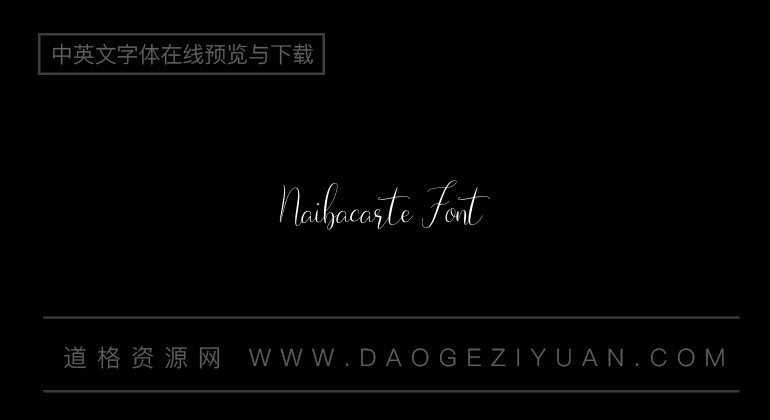
Naibacarte Font
Naibacarte Font 是一种手工书法风格的字体,设计师将其设计为一种有机、自然的字体类型。它的风格灵感来源于手工书法,具有浓郁的艺术气息。这种字体的笔画流畅,线条自然,它的字形并不是完全规则的,这样的设计使得它看起来更加真实、有生动感。Naibacarte Font 字体适用于设计印刷品、标志和海报等场合。
Naibacarte Font是一款非常不错的手写艺术字体,具有很好的视觉感,适合于文化类的宣传设计、商业类品牌的广告和产品包装设计以及个性化文字排版等较多场景。